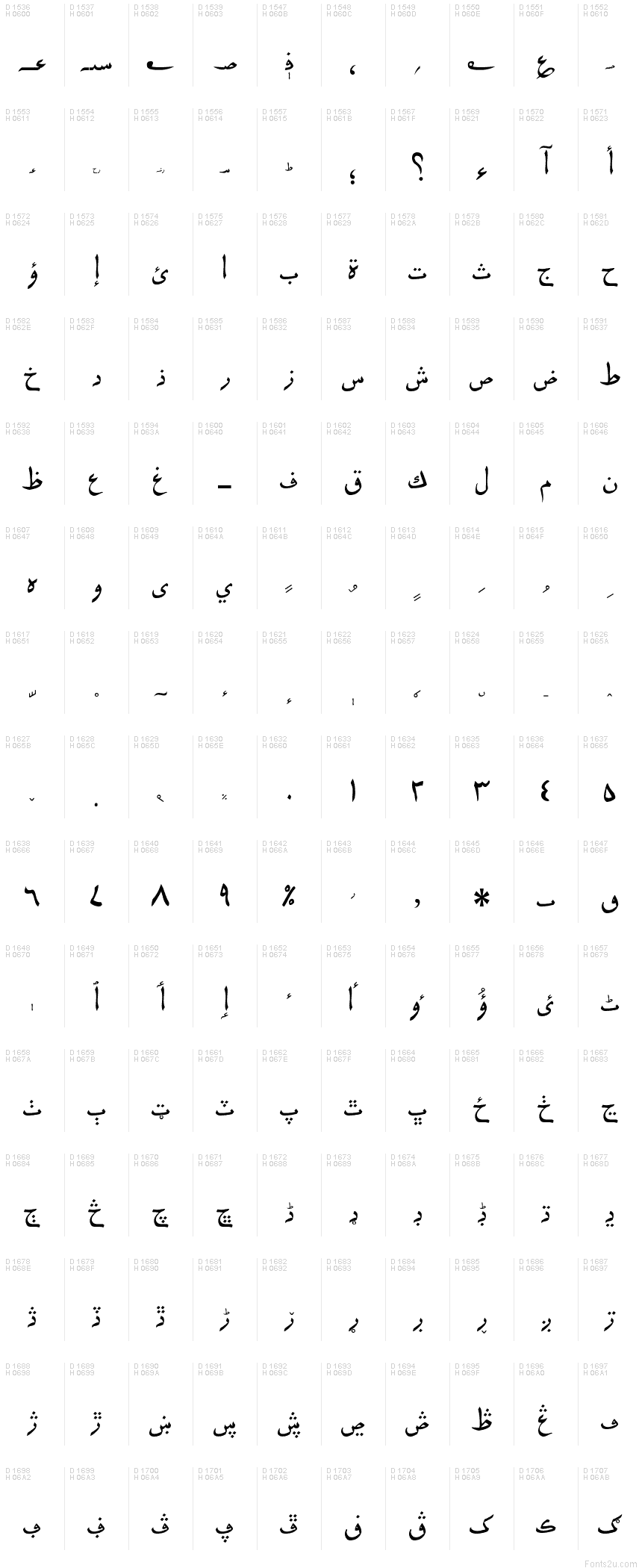
PakType Tehreer 字体
PakType Tehreer
PakType Tehreer 由 Mohammad Hanif 设计,是一款免费的阿拉伯语书法字体,带有手写新闻标题的质感。其字形紧凑且充满活力,笔画末端收尖,转折锐利,并带有向右流动的动感,为文字赋予了一种快捷的编辑排版节奏,而非刻板、严肃的碑刻风格。
这种活力使其非常适合用于乌尔都语和阿拉伯语的刊头、文化海报、书籍封面、杂志标题及标题卡片,这些场景往往需要文字兼具表现力和可读性。作为一款免费字体,它也非常适用于简短引语、章节开头以及需要借助其快速、手写感特征的品牌设计工作。